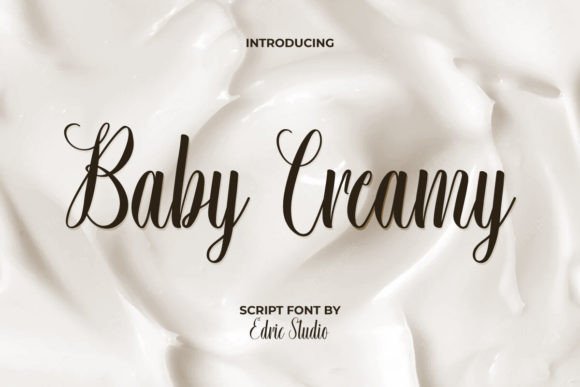
Baby Creamy
適切なデザイン要素を見つけるのは難しい場合がありますが、Baby Creamyは作品を即座に引き立てる優れたコレクションを提供します。
POD(オンデマンド印刷)製品、結婚式の招待状、またはソーシャルメディアのグラフィックを作成している場合でも、Baby Creamyは理想的です。